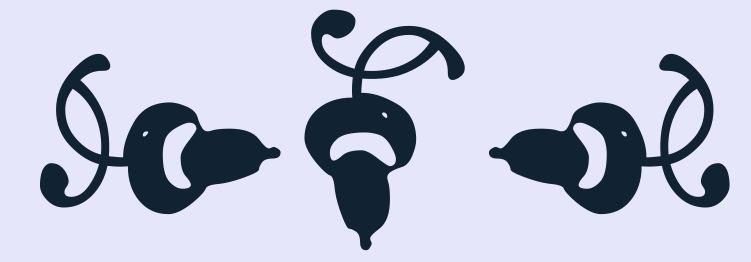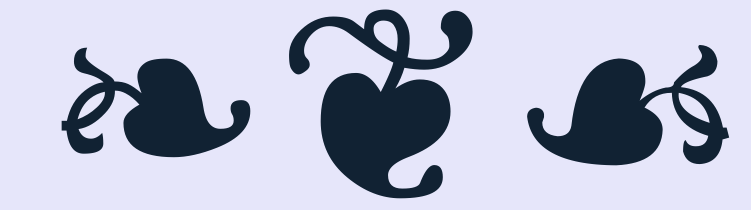
Suche nach Schriften mit Aldus-Blatt ❦
ich durchforste grad händisch meine kleine Schrift-Sammlung und die Online-Resourcen nach Schriften mit Aldus-Blatt.
Ich würde gerne als Gestaltungselement das Aldus-Blatt einsetzen.
Habt ihr ein paar Schriften wie die Bembo/Cardo u.ä. in Petto,  um eine kleine Liste anzulegen?
Gibt es da eigentlich Variationen im Sinne des Stils der Schrift? Oder besticht das Aldusblatt ❦ in seiner Form als Alternative zum Alinea ¶  und hat gar keine verschiedenen Ausprägungen?
Variationen
☙ U+2619 REVERSED ROTATED FLORAL HEART BULLET
❦ U+2766 FLORAL HEART
❧ U+2767 ROTATED FLORAL HEART BULLET
Die Junicode hat Eicheln? :-?
Die soll ja auch Mittelalterinteressierten dienen, da findet sich auf der WP-Seite zum Aldusblatt auch eine eichelige Vorlage, scheint früher eine normale Form gewesen zu sein?